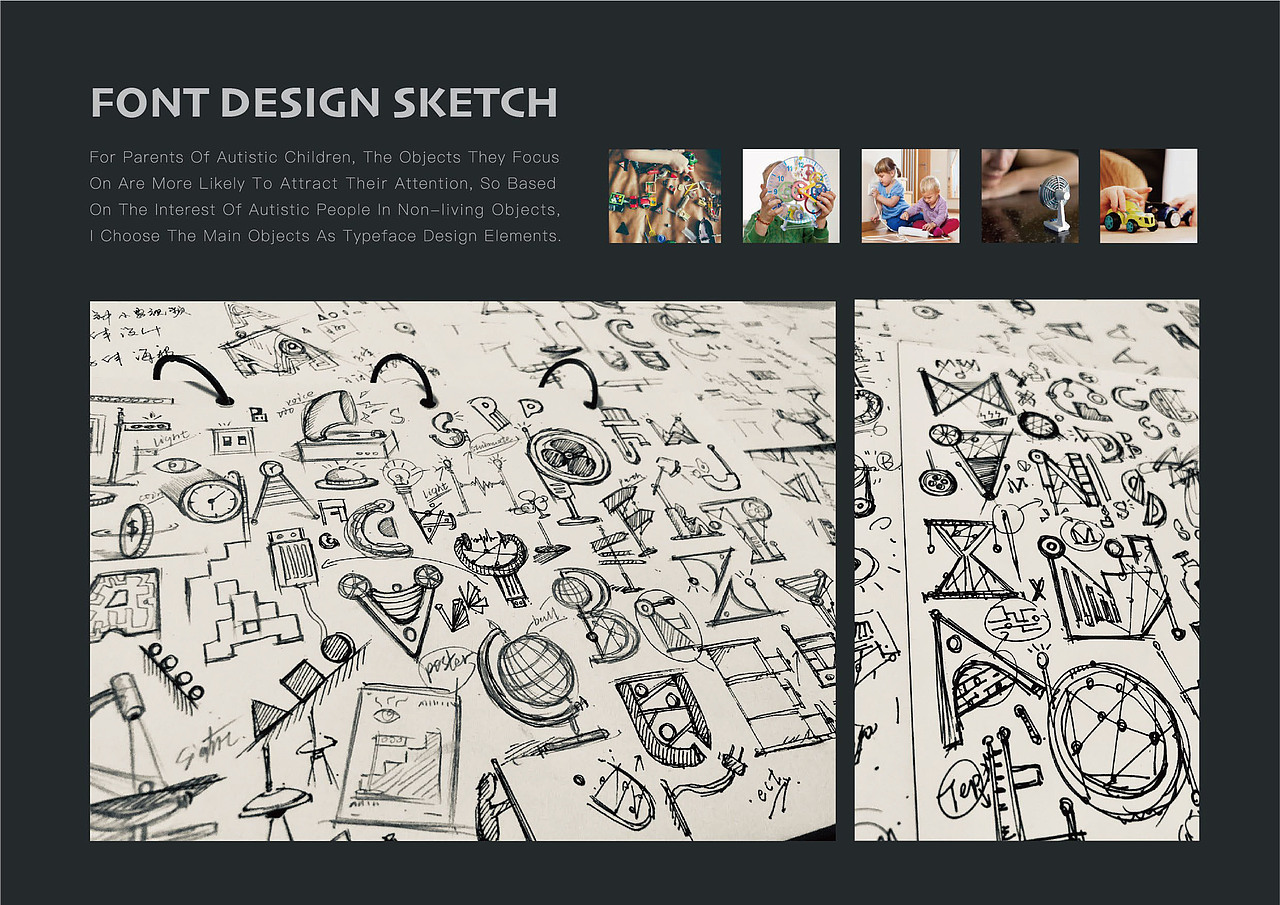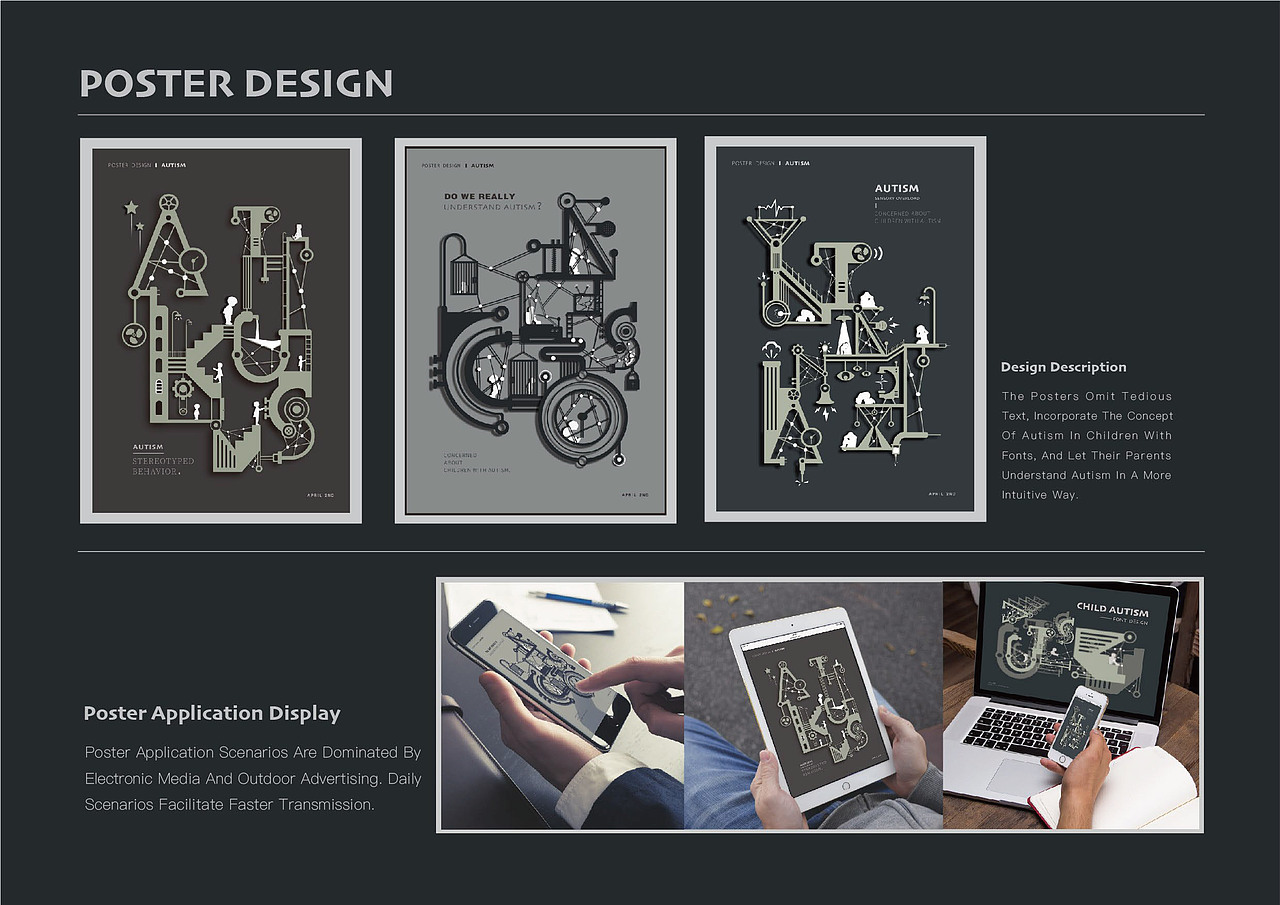
自闭症字体、海报设计
《中国自闭症教育服务行业发展状况报告》显示,目前中国自闭症患者已超1000万,0到14岁的儿童患病者可能就超过200万。自闭症儿童的数量飞速增加,但社会大众似乎并不关注和了解这群来自“星星的孩子”们。
这是一个缺乏社会关怀的群体。目前,孤独症病例远远超过人们的估计。许多自闭症儿童父母对自闭症的认识不够清晰,在对儿童的指导、教育和治疗等方面造成了很大的误解。此次设计通过字体和海报形式展现,希望能让更多的人们了解和关注自闭症儿童,走进他们的内心世界。
了解自闭症的现状和发展状态,通过分析世界范围内的自闭症儿童的男女比例,以及各国家地区的自闭症儿童历年增长趋势做出了以下数据图表,这里主要分析了我国自闭症儿童数量的增长状态。
主要分析出自闭症儿童行为的四大特点,语言障碍、社交障碍、行为刻板和智力障碍。
通过向相关自闭症机构咨询,及自闭症儿童的父母的询问,找出了在日常生活中对自闭症儿童产生刺激的主要因素,其中噪音对他们的影响最大。
随后通过调查又找出了一些在日常生活中最能吸引他们注意的物品,并进行了表格统计。
通过研究发现90%的自闭症儿童都会有胃相关的问题,如消化不良等。
通过问卷调查显示了,大部分人是通过网络,身边的真实经历才了解关注自闭症群体的。
此次项目的初衷本想通过设计一些文字、智力拼图的产品帮助自闭症儿童康复,随着调研发现,很不幸的是,目前还没有治疗自闭症的最佳方法,但是能帮助和缓解自闭症的是他们的父母,所以想通过文字和海报的形式把自闭症孩子的行为和心理状态展现给他们的父母。
进行了思维导图的构建和联想。
前期的一些草图构想。
通过上述调研,在字体的设计上提取了自闭症儿童日常最为关注的物体。
自闭症海报从儿童的-行为刻板,感官刺激,自我封闭,和数据现状为主题设计。系列海报为动态设计海报,由于文件损坏暂上传图片,请大家谅解!
自闭症儿童生活中常常会关注不起眼的非生命物体,重复性的观看和摆弄。
自闭症儿童易受噪音刺激,所以在众多噪音的环境中他们会不断拍打自己的头部,甚至对自己进行肉体伤害来转移注意力
自闭症儿童常常会将自己封闭起来,缺乏与父母、朋友的沟通,通常的一个眼神接触都会让他们躲避。
通过大环境的数据展示让更多人了解、认知自闭症的现状。